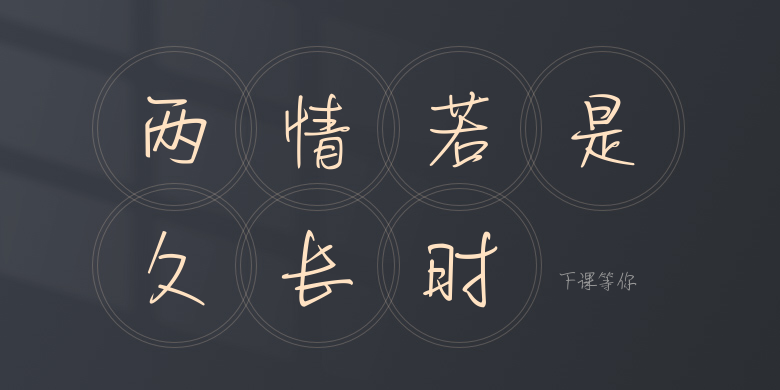
下课等你
下课等你,这款字体结构工整、笔画清晰,兼顾美观与易读性,适用于标题、正文、海报、包装、LOGO 等多种场景。字形优雅稳定,风格百搭耐看,适配日常排版与创意设计,让文字呈现更舒适、更具质感。下课等你一笔一画,皆是细节,以均衡的比例、流畅的线条打造舒适视觉体验,字形端正大气,风格简约现代。无论是商业设计、品牌宣传还是日常排版,都能轻松驾驭,让文字更有格调与力量。下课等你字体下载。